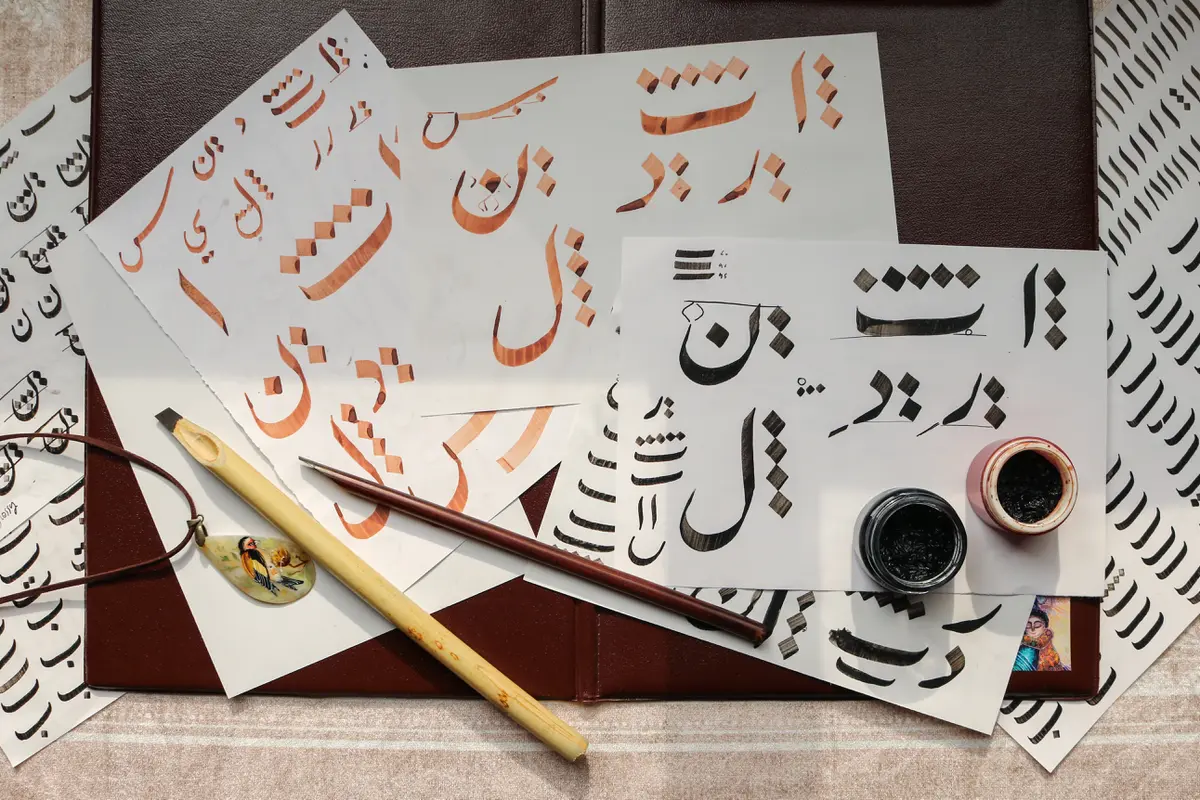
Liputan6.com, Jakarta Font Arab kerap kali dicari oleh para desainer saat adanya hari besar Islam. Hal ini tentunya untuk membuat berbagai macam desain di hari-hari penting, seperti di Bulan Ramadan, Hari Raya Idul Fitri, Hari Raya Idul Adha, Maulid Nabi, hingga Isra’ Mi’raj.Â
Font Arab digunakan tentunya bertujuan untuk menyelaraskan desain dengan nilai-nilai islami. Ada berbagai macam font Arab yang bisa kamu gunakan untuk desain. Setiap font tersebut tentunya memiliki bentuk yang berbeda-beda, jadi kamu harus memilih yang paling cocok dengan tema desain yang diusung. Â Â
Font Arab bisa berupa tulisan dengan bahasa Arab ataupun tulisan huruf abjad tapi dengan gaya huruf Arab. Kamu tentunya familier dengan tulisan Arab yang hurufnya meliuk-liuk, maka kamu juga bisa menggunakan font Arab ini dalam huruf abjad.
Berikut Liputan6.com rangkum dari berbagai sumber, Kamis (12/1/2023) tentang font Arab.
Mengenal Font
Sebelum mengenali font Arab keren untuk desain Islami, kamu perlu memahami apa itu font terlebih dahulu. Font adalah bagian penting dalam sebuah penulisan atau desain. Font adalah sekumpulan karakter teks yang dapat ditampilkan dalam gaya dan ukuran tertentu. Font dapat membuat kamu merepresentasikan sebuah tulisan dengan lebih baik sesuai tujuannya.
Ada berbagai macam font yang bisa kamu gunakan untuk berbagai tujuan. Biasanya, sudah ada berbagai macam font yang terinstal di komputer kamu. Â Namun, kamu juga bisa mendownload jenis font lainnya yang tersedia di internet. Â Jenis font ini memiliki ragam jenis dan model, terkadang tampilan dari font tersebut jauh lebih estetik dari font default di komputer.
Mengenali macam font merupakan dasar penting dalam belajar tipografi. Tipografi adalah seni mengatur huruf dan teks dengan cara yang membuat salinan terbaca, jelas, dan menarik secara visual bagi pembaca. Tipografi melibatkan macam font, tampilan, dan struktur, yang bertujuan untuk memperoleh emosi tertentu dan menyampaikan pesan tertentu.
Jenis-Jenis Font
Jenis-jenis font perlu kamu kenali sebelum mengetahui font Arab yang keren untuk desain Islami. Apalagi dengan mengetahui jenis-jenis font, tipografi dapat dibuat dengan benar. Jenis font secara mendasar terbagi dalam empat tipe, yaitu serif, sans serif, script, dan decorative.Â
Font Serif
Serif adalah macam font yang memiliki ciri khas berupa garis kecil atau stroke secara teratur melekat pada ujung huruf. Dalam tipografi, serif adalah goresan ekstra kecil yang ditemukan di akhir goresan vertikal dan horizontal utama dari beberapa huruf. Istilah "font serif" mengacu pada gaya jenis apa pun yang memiliki serif.
Font serif sangat populer dan telah ada selama bertahun-tahun. Times New Roman adalah salah satu contoh font serif. Font dengan serif sangat berguna untuk blok teks yang besar. Serif memudahkan mata untuk menelusuri teks. Sebagian besar buku, surat kabar, dan majalah menggunakan font serif untuk keterbacaannya. Font serif tidak begitu berguna untuk desain web, terutama jika digunakan dalam ukuran kecil. Karena resolusi layar beberapa monitor komputer rendah, serif kecil dapat hilang atau kabur, yang membuat teks sulit dibaca.
Font Sans Serif
Dalam tipografi, sans serif merupakan macam font yang tidak memiliki fitur perluasan yang disebut "serif" di akhir goresan. Font sans-serif cenderung memiliki variasi lebar goresan yang lebih sedikit daripada font serif. Mereka sering digunakan untuk menyampaikan kesederhanaan dan modernitas atau minimalis.
Font sans-serif telah menjadi yang paling umum untuk tampilan teks di layar komputer. Pada tampilan digital beresolusi lebih rendah, detail halus seperti serif mungkin hilang atau tampak terlalu besar. Ini membuat font sans serif lebih mudah dibaca pada tampilan digital.
Font Script
Jenis font script didasarkan pada stroke yang bervariasi dan sering kali cair yang dibuat oleh tulisan tangan. Singkatnya,font skrip adalah font yang meniru tulisan tangan. Ada dua jenis utama font skrip. Font skrip formal dan font skrip kasual. Font skrip formal adalah skrip mewah yang membangkitkan tulisan tangan master yang luar biasa. Font skrip kasual, di sisi lain, menyerupai kaligrafi hanya dengan sedikit sapuan.
Font Decorative
Ini adalah kategori terbesar dan juga paling beragam. Jarang digunakan untuk blok teks yang panjang, tipografi dekoratif populer untuk signage, headline dan situasi serupa pernyataan tipografi yang kuat yang diinginkan. Macam font decorative sering mencerminkan aspek budaya – seperti tato atau grafiti – atau membangkitkan keadaan pikiran, periode waktu, atau tema tertentu.
Beberapa jenis dekoratif digambar tangan atau mungkin dibuat dari jenis digital yang telah dimanipulasi dalam editor font atau program grafis agar sesuai dengan tujuan tertentu seperti papan nama buletin atau logo. Ada banyak contoh font dekoratif seperti Calligraphy, Tattoo, Cursive, Lettering, Handwriting, dan masih banyak lagi.
Font Arab untuk Desain Islami
:strip_icc():format(webp)/kly-media-production/medias/4289519/original/053617400_1673524286-pexels-mart-production-7333600.jpg)
Font Arab untuk desain Islami tentunya lebih mengarah kepada jenis font decorative. Hal ini karena font Arab ini digunakan untuk desain dan bertujuan agar desain tersebut dapat memunculkan suasana yang Islami atau budaya Arab.
Font Arab biasanya digunakan saat kamu membuat desain bertemakan Hari Raya Idul Fitri, Hari Raya Idul Adha, bulan Ramadan, Maulid Nabi, hingga Isra’ Mi’raj. Font Arab tentunya dapat merepresentasikan desain tersebut sebagai desain memperingati hari raya Islam. Melansir 1001fonts.com, berikut beberapa font Arab untuk desain islami yang bisa kamu gunakan:
- Ceria Lebaran by Gunarta
- Kahfi by nurfdesigns
- Zanzabar by Sharkshock
- Sinbad the Sailor by vladimirnikolic
- Bismillah Script by Mikrojihad
- Lalezar by Borna Izadpanah
- Al Athara Sabil by ghielzact
- Shayan by typefactory
- Sparkling Khufis by Dafsyaja
- La Gagliane by Hishand-Studio
- Ramadhani by eknoji
- An Nisa by Mevstory Studio
- Zefir by stormag
- Basmala by afkaristudio
- albarokah by NeutroneLabs
- Rabiul Free Trial by typefactory
- Hakan Free Trial by typefactory
- Ramadhanfest by andikafez
- Blessed Eid Demo by CalligraphyFonts
- Shalleh by Akifatype
- Arabica by Manuel Ramos
- Delik Free Trial by typefactory
- Assyam by typotopia
- Marhaban by Alpaprana
- Marhaban Ramadhan DEMO by Omotu Studio
- Astaghfirulloh Demo by VinType
- Miracle Ramadhan by Alpaprana
Â
Baca informasi kesehatan terbaru di Kesehatan Liputan6
Advertisement
:strip_icc():format(webp)/kly-media-production/medias/9385238/original/034787500_1793247276-Cek_Fakta__Tidak_Benar_Ini_Link_Pendaftaran__7_.jpg)
:strip_icc():format(webp)/kly-media-production/medias/9359577/original/013031200_1790564633-Cek_Fakta_Tidak_Benar_Ini_Link_Pendaftaran_-_2026-09-28T100252.716.jpg)
:strip_icc():format(webp)/kly-media-production/medias/9391176/original/070792400_1793875895-Screenshot_2026-11-05_170652.jpg)
:strip_icc():format(webp)/kly-media-production/medias/8259592/original/057928600_1781507421-guru_sekolah_rakyat_-_cek_fakta.jpg)
:strip_icc():format(webp)/kly-media-production/medias/4087423/original/040314200_1657694277-pexels-mona-termos-3139298.jpg)
:strip_icc():format(webp)/kly-media-production/medias/9391954/original/072137000_1793958689-Vertical_500x656_-_Dayatana.png)
:strip_icc():format(webp)/kly-media-production/medias/9345690/original/067748100_1789050705-WhatsApp_Image_2026-09-10_at_21.02.17.jpeg)
:strip_icc():format(webp)/kly-media-production/medias/9344472/original/056989200_1788947104-WhatsApp_Image_2026-09-09_at_4.34.59_PM.jpeg)
:strip_icc():format(webp)/kly-media-production/medias/9329986/original/052581700_1787307659-WhatsApp_Image_2026-08-21_at_17.03.26.jpeg)
:strip_icc():format(webp)/kly-media-production/medias/9308204/original/009529000_1785132477-WhatsApp_Image_2026-07-27_at_12.46.15_PM.jpeg)
:strip_icc():format(webp)/kly-media-production/medias/9304577/original/005200700_1784721544-WhatsApp_Image_2026-07-22_at_18.12.19.jpeg)
:strip_icc():format(webp)/kly-media-production/medias/9291253/original/086637400_1783510555-WhatsApp_Image_2026-07-08_at_17.07.14.jpeg)
:strip_icc():format(webp)/kly-media-production/medias/9290264/original/065273200_1783441564-WhatsApp_Image_2026-07-07_at_20.36.04.jpeg)
:strip_icc():format(webp)/kly-media-production/medias/9290208/original/083376600_1783432448-WhatsApp_Image_2026-07-07_at_20.29.47.jpeg)
:strip_icc():format(webp)/kly-media-production/medias/9290170/original/059488200_1783429797-WhatsApp_Image_2026-07-07_at_19.50.54.jpeg)
:strip_icc():format(webp)/kly-media-production/medias/9271167/original/049315200_1783170039-WhatsApp_Image_2026-07-04_at_17.30.33.jpeg)
:strip_icc():format(webp)/kly-media-production/medias/8974535/original/013451500_1782983178-1106e511-c5ef-46a5-8b74-de1fd75e92f8.jpg)
:strip_icc():format(webp)/kly-media-production/medias/8262336/original/070728700_1781780140-WhatsApp_Image_2026-06-18_at_17.41.22.jpeg)
:strip_icc():format(webp)/kly-media-production/medias/5447736/original/015145700_1765962219-Vertical_500x656_-_SIXtainability.png)
:strip_icc():format(webp)/kly-media-production/medias/9292496/original/090511000_1783600392-NTB_Karbon.jpeg)